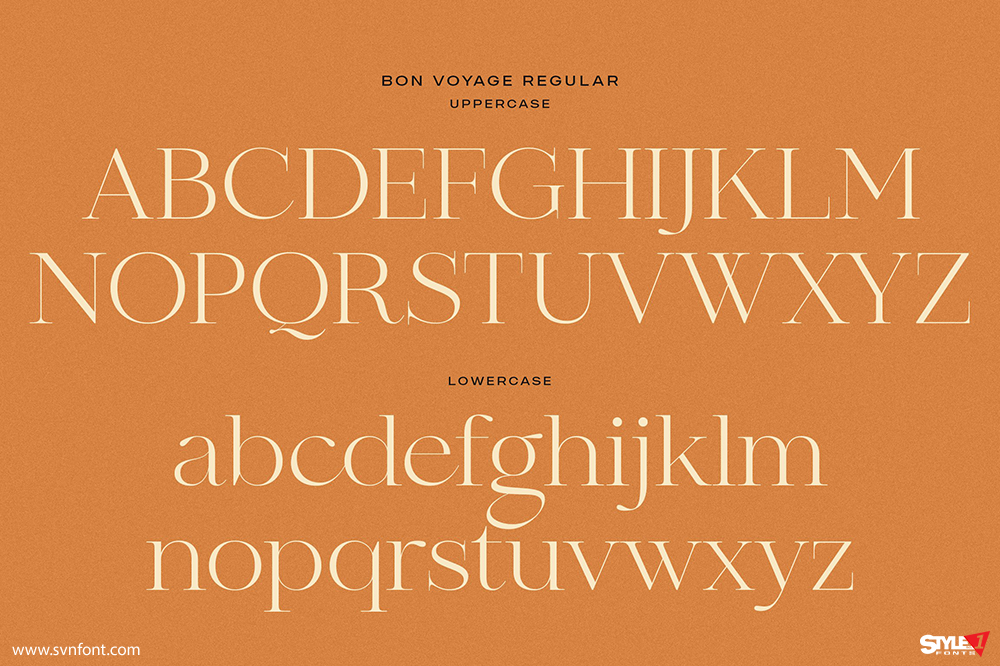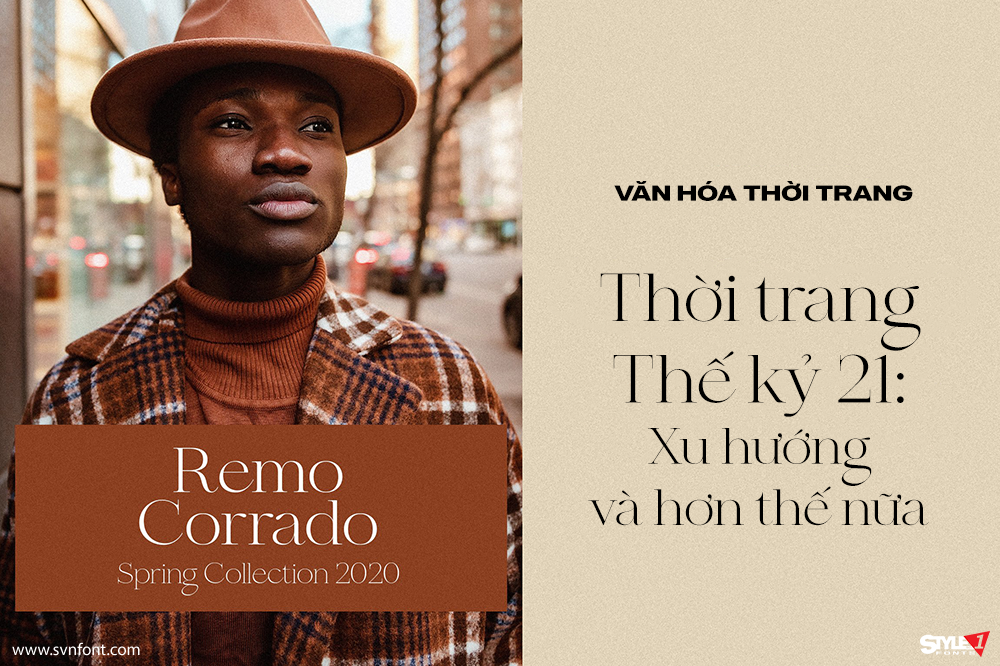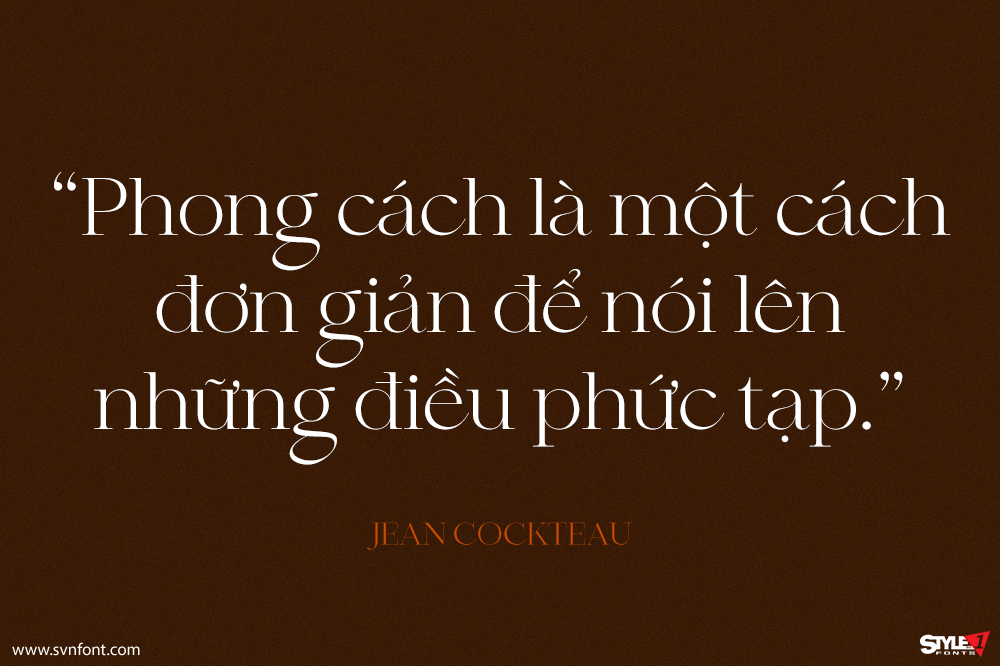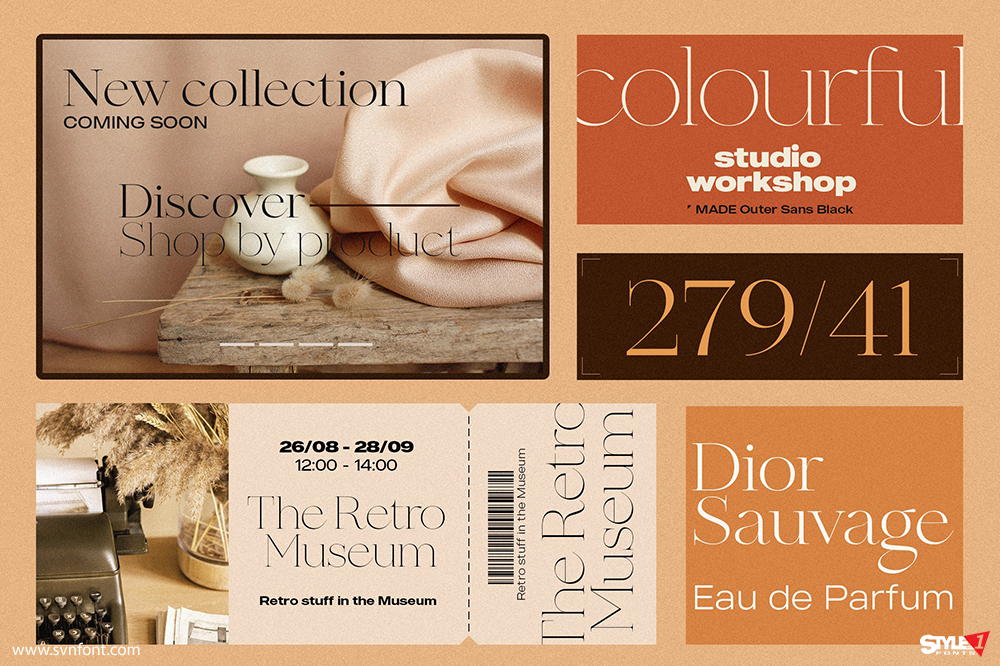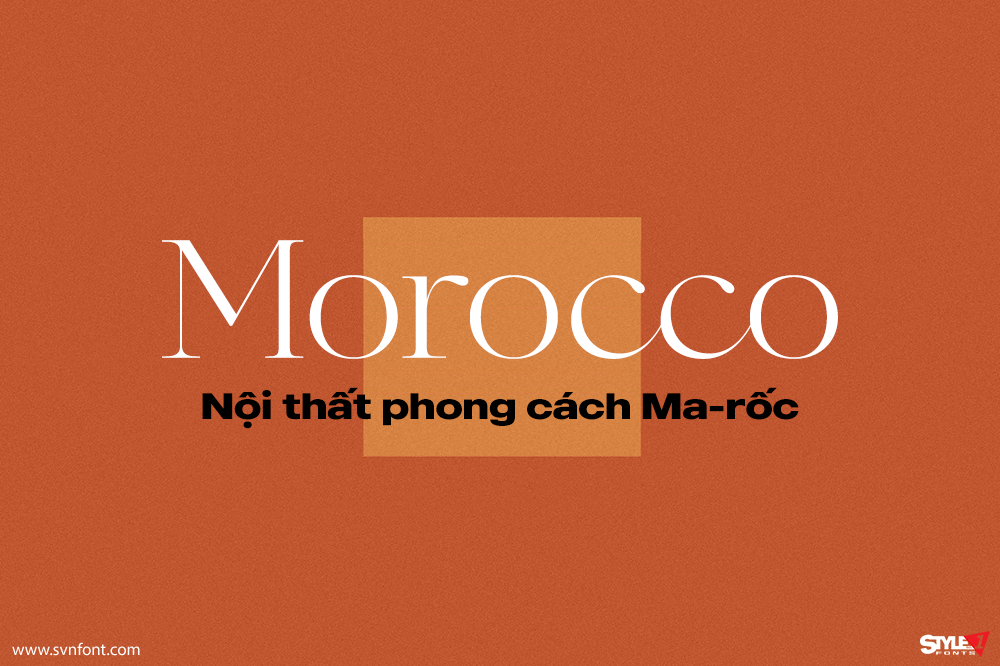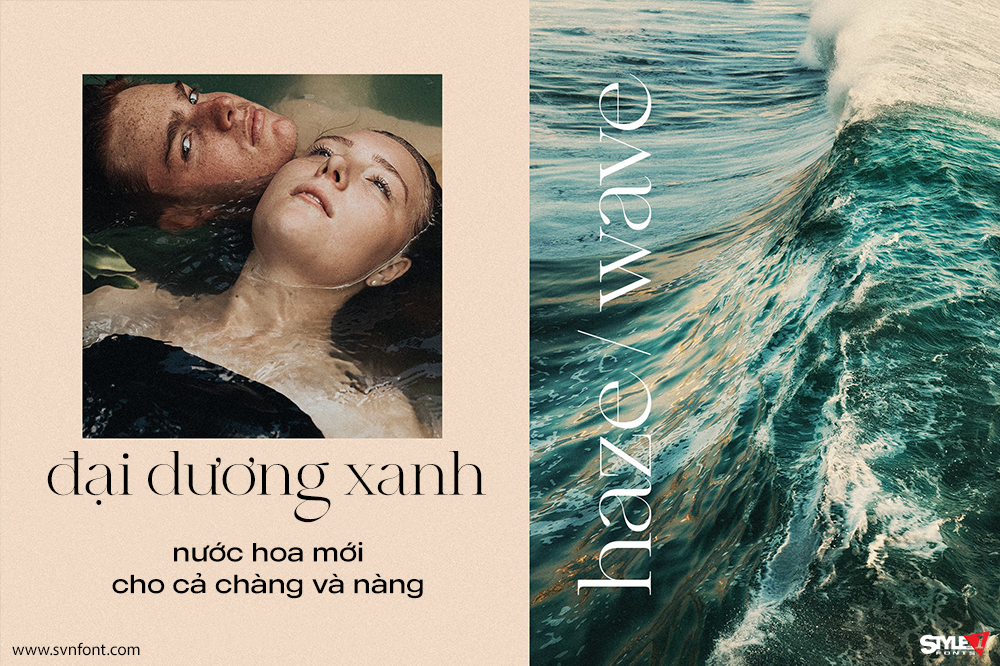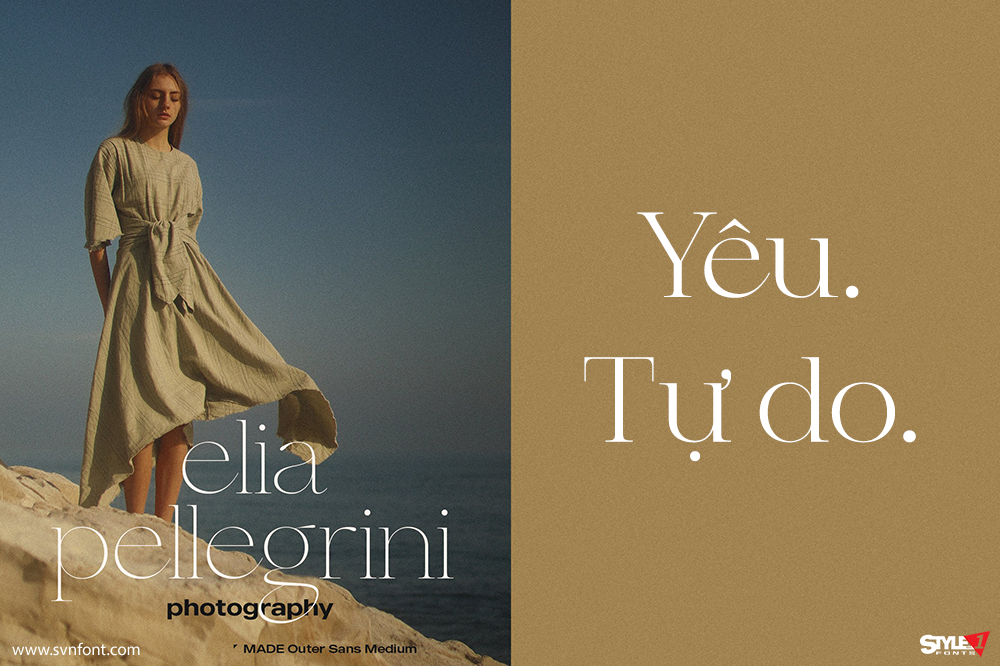
Bon Voyage là một typeface serif thư pháp hiện đại. Đây là lựa chọn lý tưởng cho các designer và creative đang tìm kiếm một font thư pháp chất lượng để sử dụng trong thiết kế đồ họa, ấn phẩm in ấn hoặc tạp chí. Bon Voyage đáp ứng hoàn hảo những nhu cầu đó với phong cách thanh lịch và giàu tính thẩm mỹ.
Nhà thiết kế: MadeType
Nhà phát hành: Made Type